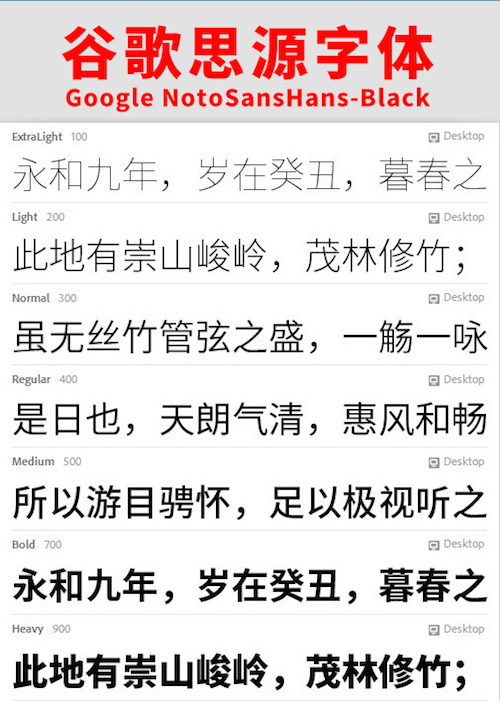
思源黑體是Adobe與Google歷時三年在2014年7月宣布推出的一款開源字體,這是一款新的供桌面使用的開源 Pan-CJK 字體家族, 有七種字體粗細(ExtraLight、Light、Normal、Regular、Medium、Bold 和 Heavy),完全支持繁體中文、簡體中文、日文和韓文,這些全部都包含在一種字體中。它還包括來自我們頗受歡迎的 Source Sans字體家族的拉丁文、希臘文和西里爾文字形。